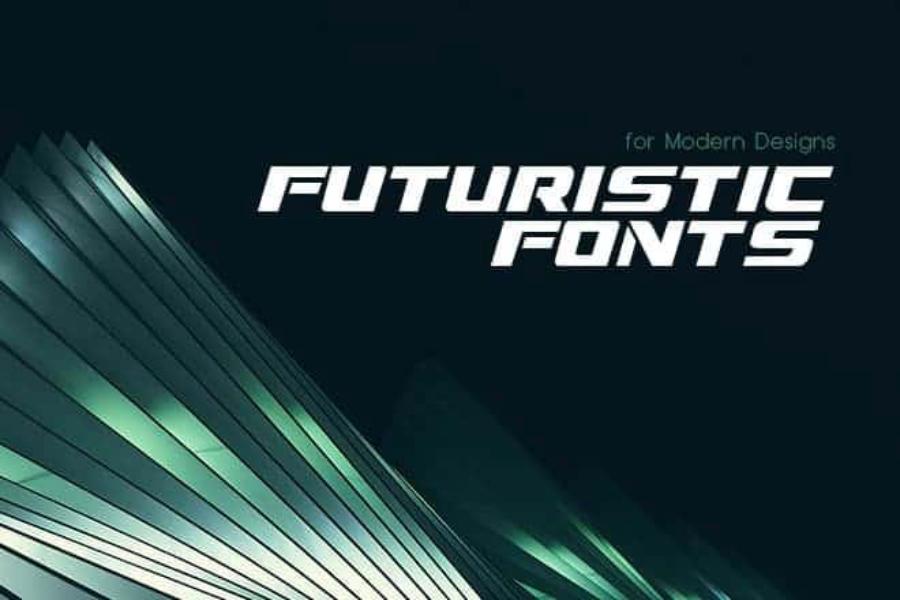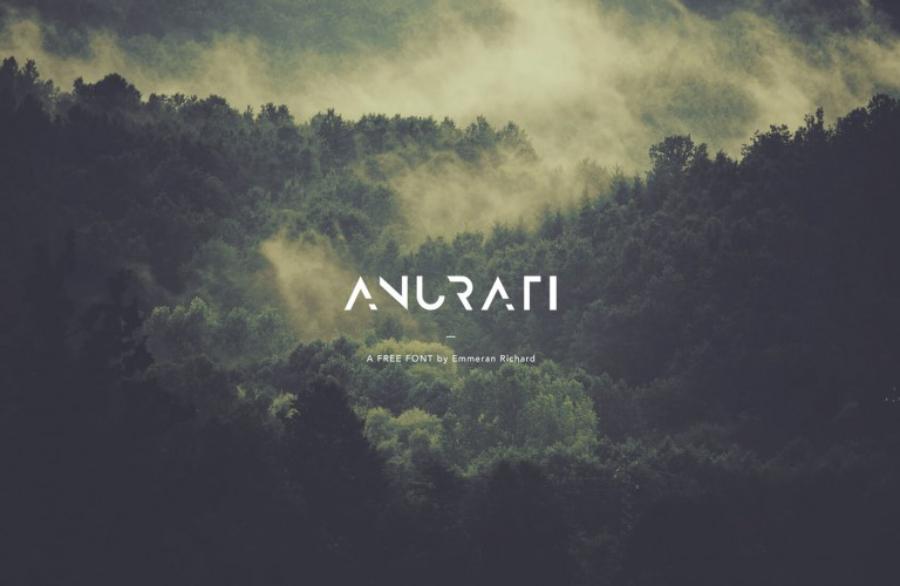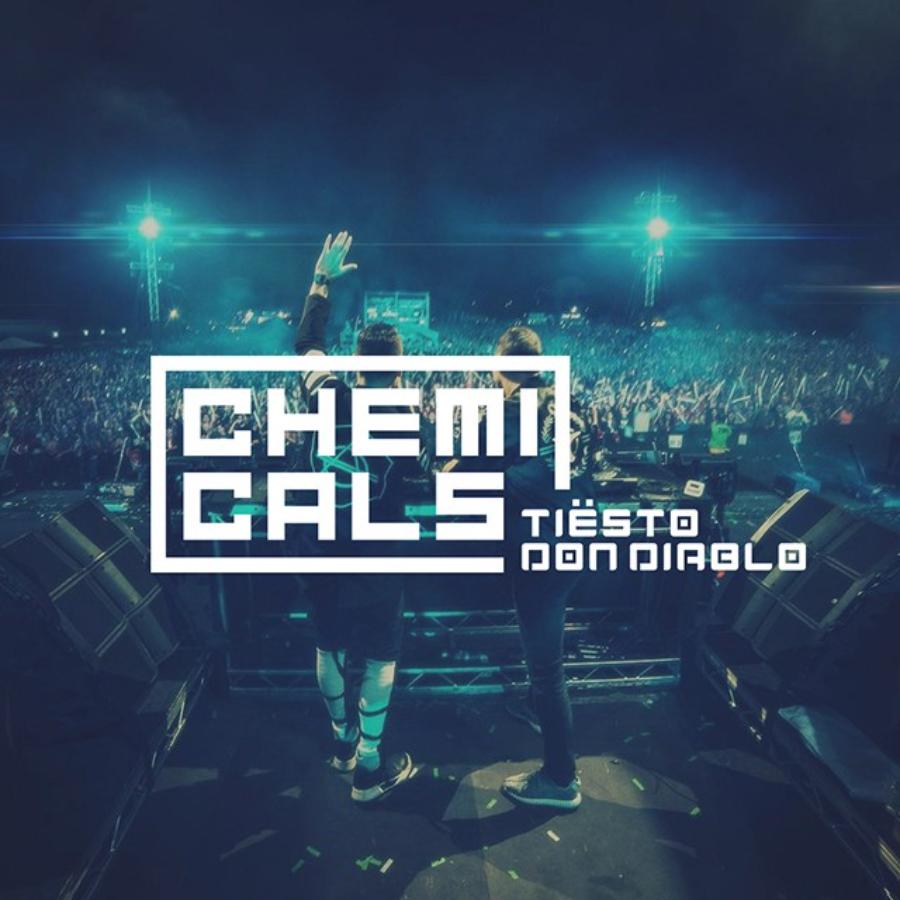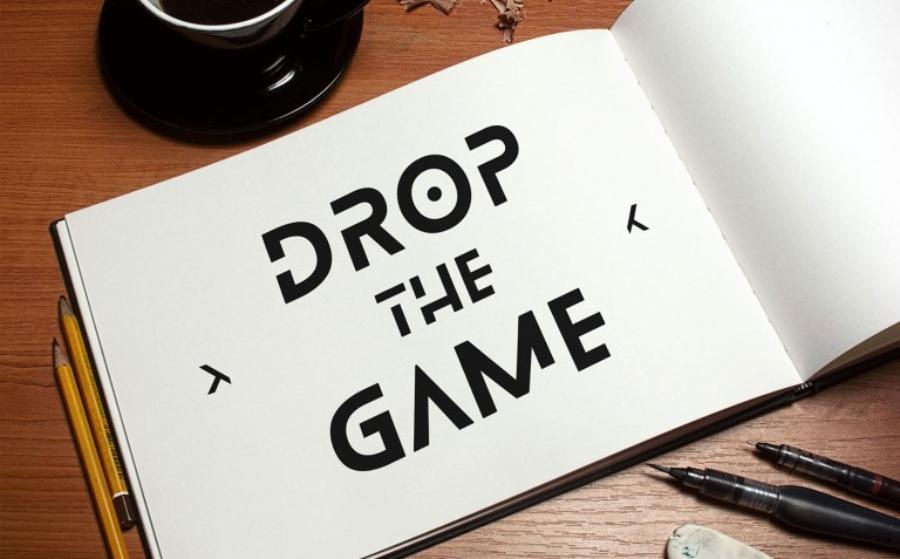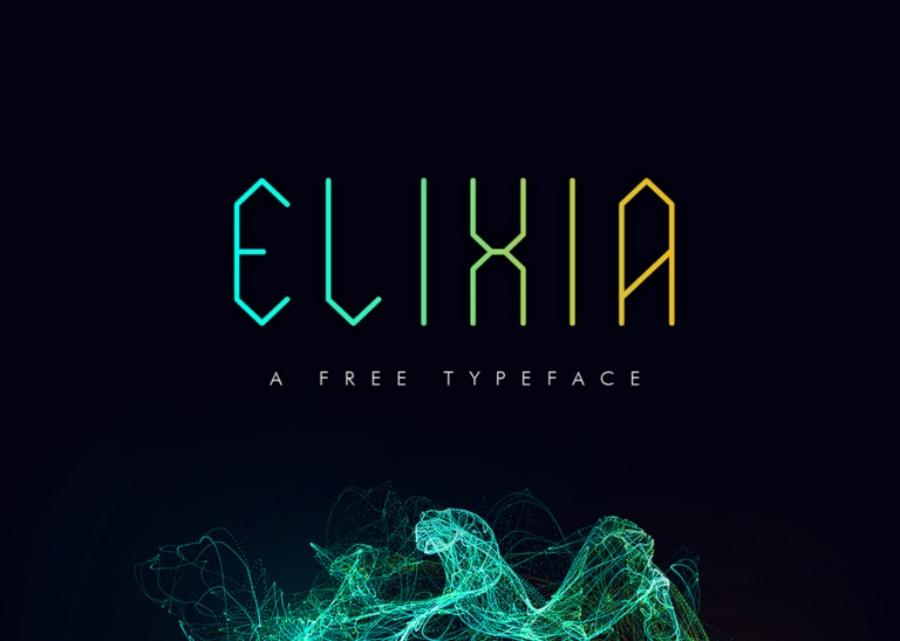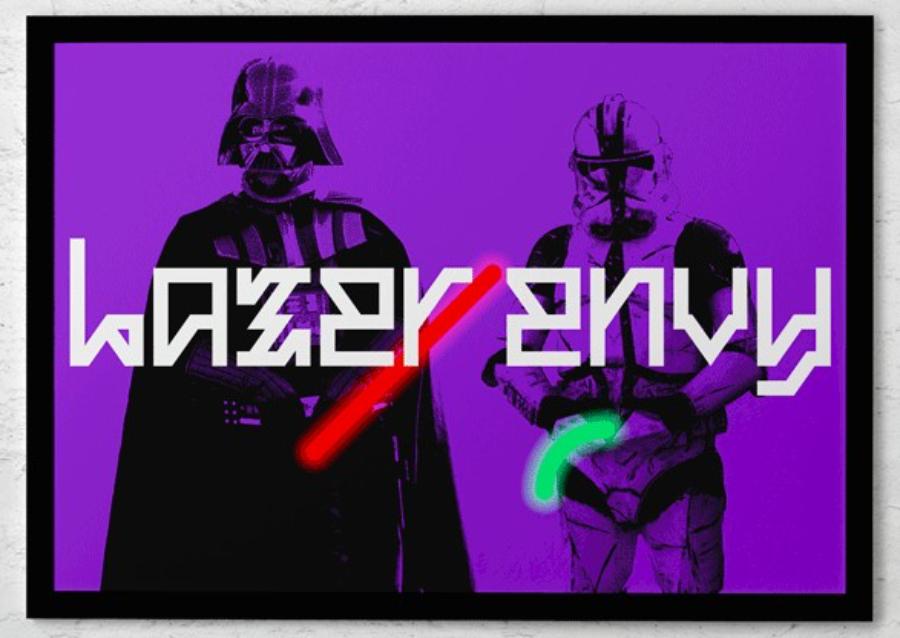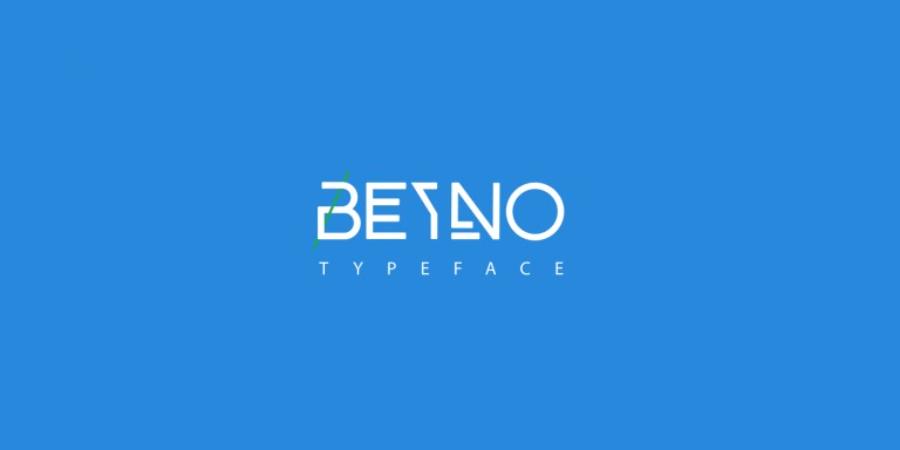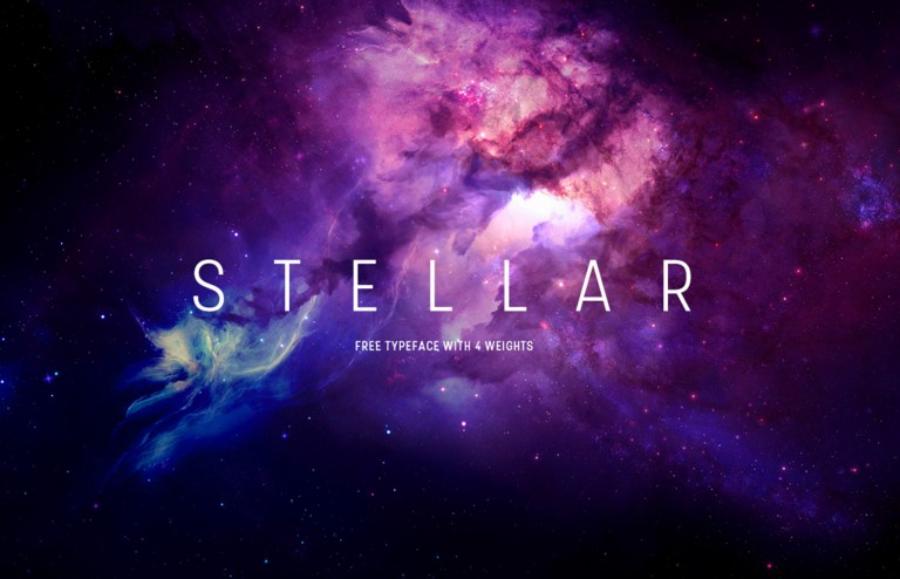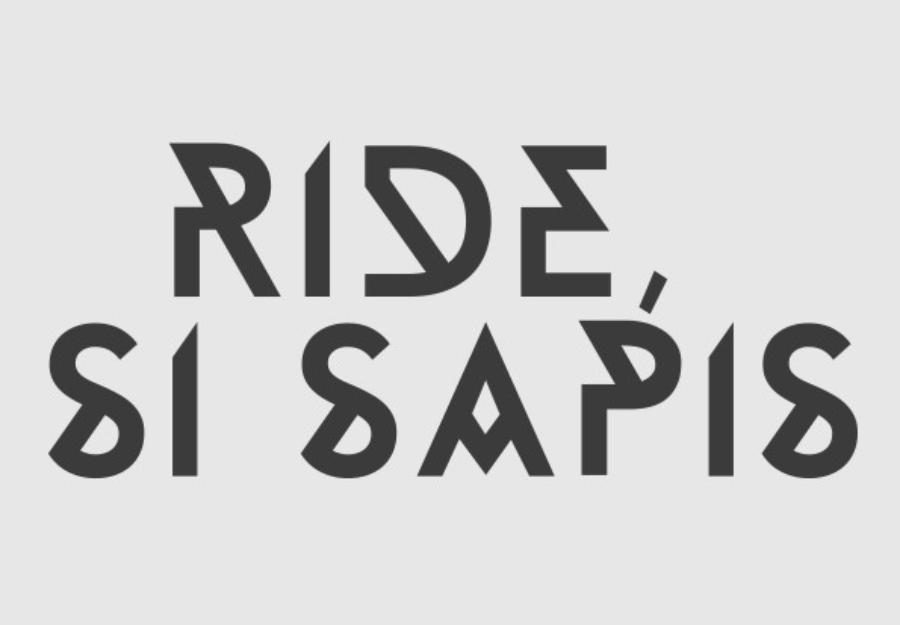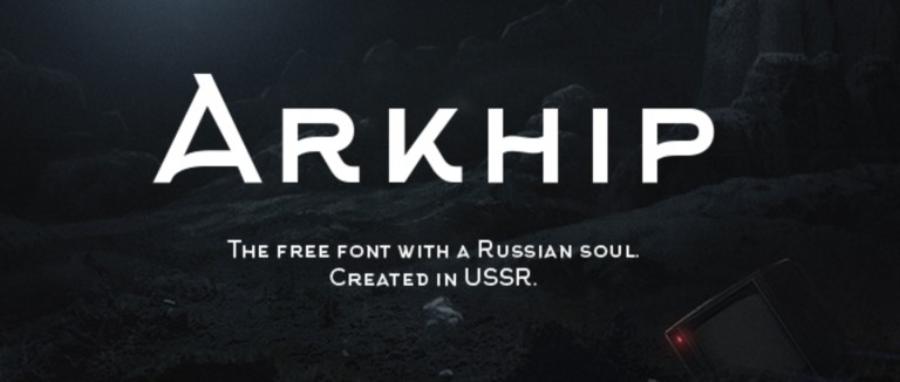
Futuristic Font Là Gì? Top 9 Font Futuristic Cực Kỳ Ấn Tượng Bạn Nên Biết
Một trong những phong cách font chữ đang trở thành xu hướng hiện nay đó chính là Futuristic Font – những kiểu chữ mang đậm chất công nghệ và tương lai. Bài viết sau, Sadesign sẽ giúp bạn hiểu Futuristic Font là gì và giới thiệu Top 9 font Futuristic cực kỳ ấn tượng, đây là những lựa chọn tuyệt vời cho các dự án thiết kế hiện đại.
1. Futuristic Font là gì?
Futuristic Font, hay còn gọi là font chữ tương lai, là một phong cách thiết kế font mang đậm tính hiện đại và công nghệ. Các font này thường được đặc trưng bởi các đường nét sắc sảo, mạnh mẽ và đôi khi là những hình học trừu tượng, tạo ra cảm giác như đến từ một thế giới tương lai. Futuristic Font không chỉ đơn thuần là những kiểu chữ đẹp mà còn truyền tải thông điệp về sự đổi mới và sáng tạo.
Các font chữ này phù hợp với những dự án có chủ đề về công nghệ, khoa học viễn tưởng, hay bất kỳ lĩnh vực nào cần truyền tải cảm giác hiện đại và tiên tiến. Chúng thường được sử dụng trong thiết kế logo, poster phim, trang web công nghệ, ứng dụng di động, và thậm chí là quảng cáo.
Những đặc điểm nổi bật của Futuristic Font bao gồm:
• Đường nét sắc sảo: Các chữ cái thường có những cạnh nhọn, đường cong mượt mà hoặc các góc cạnh độc đáo.
• Tính đối xứng: Futuristic Font thường có tính đối xứng hoặc các yếu tố hình học, tạo cảm giác ổn định và cân đối.
• Hạn chế sự phức tạp: Font này thường tránh sự rườm rà và phức tạp, thay vào đó là sự tối giản và dễ đọc.
Khi sử dụng Futuristic Font trong thiết kế, bạn đang mang lại sự mới mẻ và sự nổi bật, giúp dự án của mình có thể dễ dàng thu hút sự chú ý từ người nhìn.
2. Top 9 Font Futuristic Cực kỳ ấn tượng
Dưới đây sẽ list 9 font chữ futuristic cực kỳ ấn tượng, mang đến cho bạn những lựa chọn tuyệt vời để làm nổi bật dự án thiết kế của mình.
2.1. ANURATI
ANURATI là một trong những font Futuristic nổi bật được thiết kế với sự kết hợp giữa sự hiện đại và sự sáng tạo. Font này có các đường nét mảnh mai và thanh thoát nhưng lại vô cùng ấn tượng, với sự đặc trưng là các hình học và sự tỉ mỉ trong từng chi tiết. ANURATI thường được lựa chọn cho các dự án muốn tạo ra cảm giác của một thế giới tương lai đầy đổi mới.
Font ANURATI không chỉ gây ấn tượng bởi sự độc đáo mà còn bởi khả năng dễ đọc. Với thiết kế sắc nét, các chữ cái được tạo ra với các góc cạnh tinh tế, mang lại vẻ đẹp vừa mạnh mẽ vừa thanh thoát. Đây là một font chữ tuyệt vời để sử dụng trong các thiết kế mang tính chất công nghệ cao, từ logo đến banner quảng cáo, hay thậm chí là các trang web có chủ đề khoa học viễn tưởng.
Đặc điểm nổi bật của ANURATI:
• Thiết kế tối giản: Các đường nét của font chữ này được tối giản để dễ dàng nhận diện và không gây phân tâm cho người đọc.
• Phong cách hiện đại: ANURATI mang đậm phong cách hiện đại, phù hợp cho các thiết kế mang tính chất sáng tạo và đổi mới.
• Dễ đọc: Mặc dù có vẻ ngoài độc đáo, ANURATI vẫn giữ được tính dễ đọc, giúp các dự án sử dụng nó đạt được mục tiêu truyền tải thông điệp một cách rõ ràng.
2.2. ATLANTICO
ATLANTICO là một font Futuristic có thiết kế mạnh mẽ và đặc biệt phù hợp với những dự án yêu cầu tính chất công nghệ và hiện đại. Với các đường nét sắc sảo và sự kết hợp của các yếu tố hình học, ATLANTICO mang lại một cảm giác đầy sức mạnh và tựa như những chữ cái được lấy từ một tương lai đầy hứa hẹn.
Font này thích hợp cho các dự án mang tính năng động và hiện đại, như thiết kế logo cho các công ty công nghệ, các ứng dụng di động, hoặc các sản phẩm sáng tạo liên quan đến lĩnh vực khoa học viễn tưởng. ATLANTICO có thể tạo ra ấn tượng mạnh mẽ ngay từ cái nhìn đầu tiên nhờ sự kết hợp giữa các góc cạnh sắc nét và các đường thẳng mạnh mẽ, mang đến cảm giác như một nền tảng công nghệ tiên tiến.
Đặc điểm nổi bật của ATLANTICO:
• Phong cách hình học: ATLANTICO sử dụng các yếu tố hình học rõ rệt, với các đường thẳng và góc cạnh mang lại sự vững chắc và ổn định.
• Tính động lực: Đây là một font chữ lý tưởng cho các dự án cần sự mạnh mẽ và đầy năng lượng.
• Sự nổi bật: Font này có thể dễ dàng làm nổi bật thông điệp của một thương hiệu hoặc dự án với thiết kế mạnh mẽ và đầy cá tính.
2.3. BLANKA
BLANKA là một font Futuristic có thiết kế đơn giản nhưng đầy tính nghệ thuật. Với những đường nét mềm mại nhưng không kém phần hiện đại, BLANKA mang đến sự thanh thoát và dễ dàng kết hợp với các yếu tố thiết kế khác. Đây là một font lý tưởng cho những ai tìm kiếm sự tối giản nhưng vẫn muốn có một thiết kế ấn tượng và khác biệt.
BLANKA không chỉ đẹp mắt mà còn rất dễ sử dụng trong nhiều loại thiết kế khác nhau, từ các trang web đến các ấn phẩm quảng cáo. Sự kết hợp của các đường cong nhẹ nhàng cùng với những nét cắt tinh tế tạo ra sự mềm mại, dễ chịu cho người nhìn mà không kém phần hiện đại.
3. Kết luận
Futuristic Font là sự kết hợp hoàn hảo giữa nghệ thuật thiết kế và công nghệ, giúp các sản phẩm thiết kế trở nên độc đáo và ấn tượng hơn. Top 9 font Futuristic Font đều mang đến những đặc trưng riêng biệt, nhưng chung một mục tiêu là tạo ra một thiết kế hiện đại, dễ đọc và phù hợp với xu hướng tương lai. Sử dụng Futuristic Font sẽ giúp nâng cao chất lượng thiết kế của bạn, từ việc tạo dựng hình ảnh thương hiệu đến việc truyền tải thông điệp một cách rõ ràng và mạnh mẽ. Nếu bạn đang tìm kiếm một phong cách thiết kế hiện đại và kho font chữ đẹp, đa dạng, đừng ngần ngại trải nghiệm ngay tại Sadesign nhé!